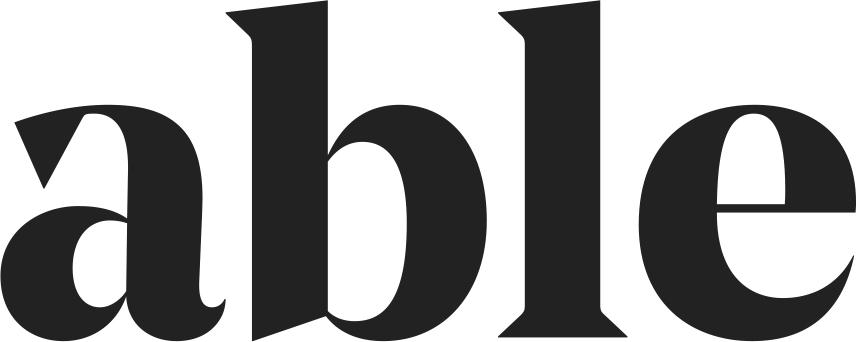
Suche eine spezielle Schriftart
kennt jemand diese Schriftart?
Heißt irgendwie "Times NewRoman (544 oder 554) identity-H" Das in Klammer bin ich nicht mehr sicher.
Ich finde allerdings in Google nichts dazu. Auch Schriftsuchmaschinen konnten mir leider nicht weiter helfen.
Kennt sie jemand?
Woher stammt das Beispiel?
Das Beispiel stammt aus einer PDF Vorlage.
@Designfreak: Danke für deine Vorschläge. Beim "b" sieht es sehr ähnlich aus, aber beim "a" leider nicht so, das ist zu rundlich. Bei dem Beispiel ist es sehr kantig.
Noe Display heißt sie.
enea design verwendet sie beispielsweise.